Em um “projeto por diversão” o designer de marca Bachir Bachchar ilustrou em divertidas palavras o verdadeiro conceito para cada uma delas.
Eu fiz essa coleção apenas por diversão, foi uma experiência divertida e boa para mim, espero que todos a possam desfrutar.
Palavras como “Hide”, “Run” e “Fall” ficaram muito mais fáceis de ser entendidas. Você pode conferir o projeto completo no Behance do Bachir, mas trouxemos algumas delas pra você.
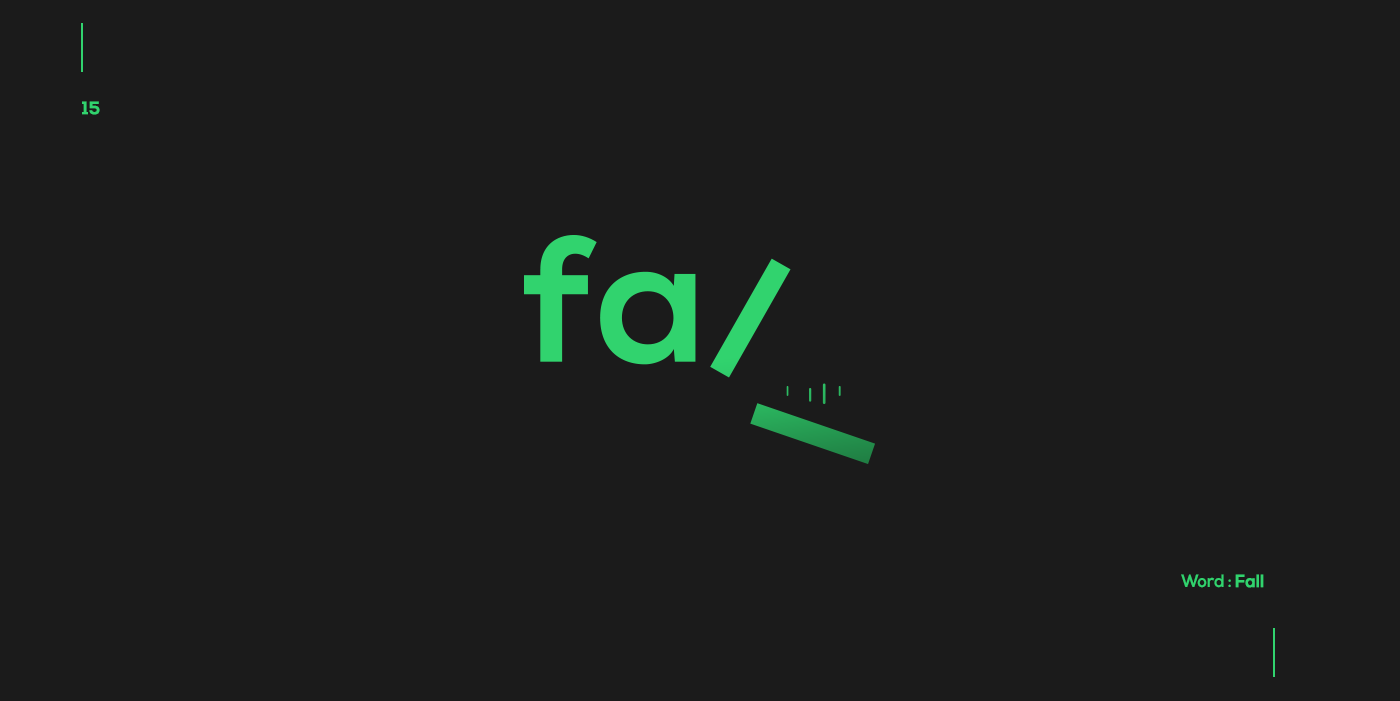
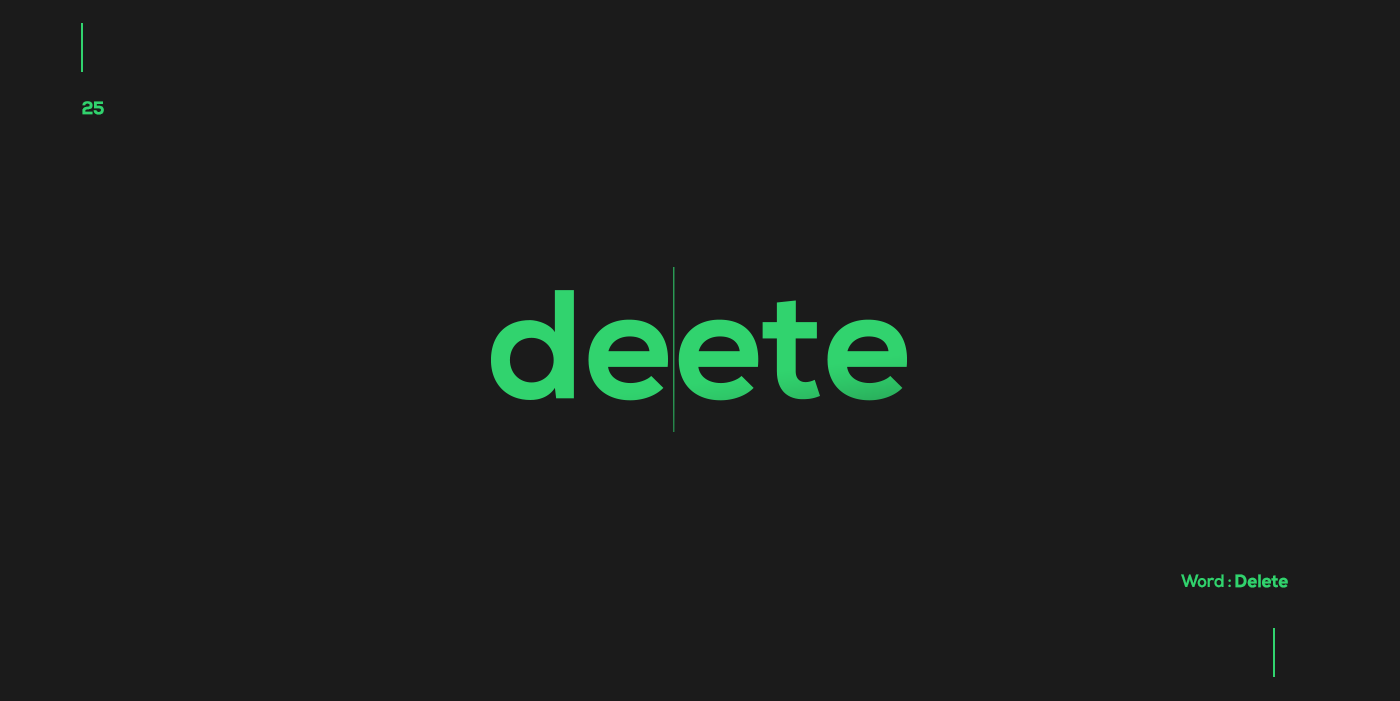
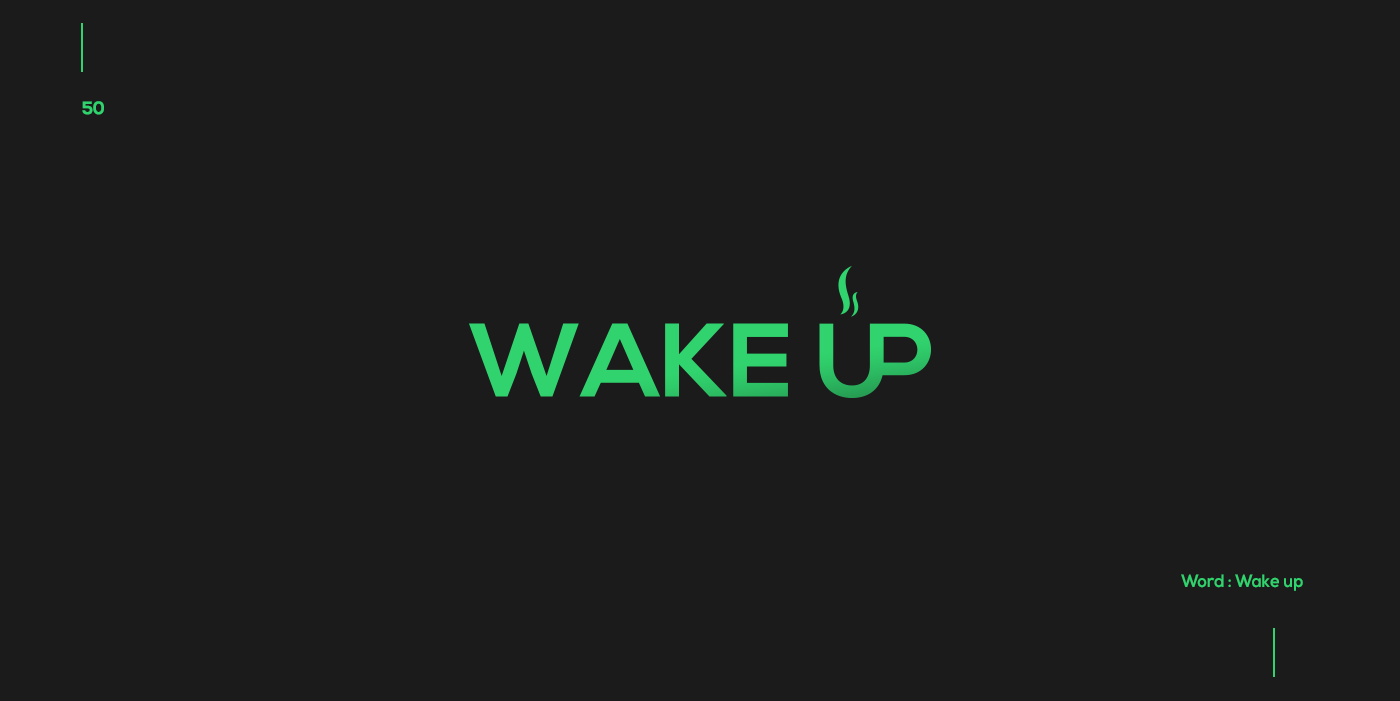
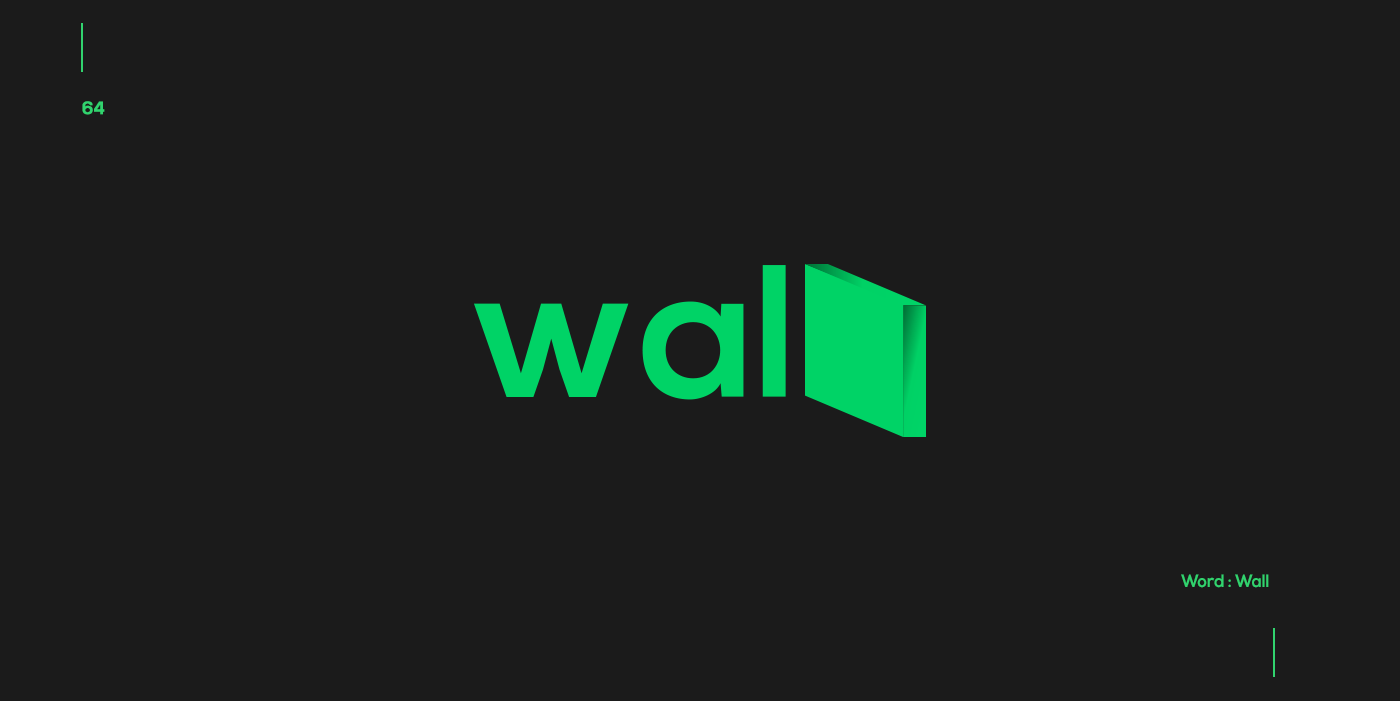
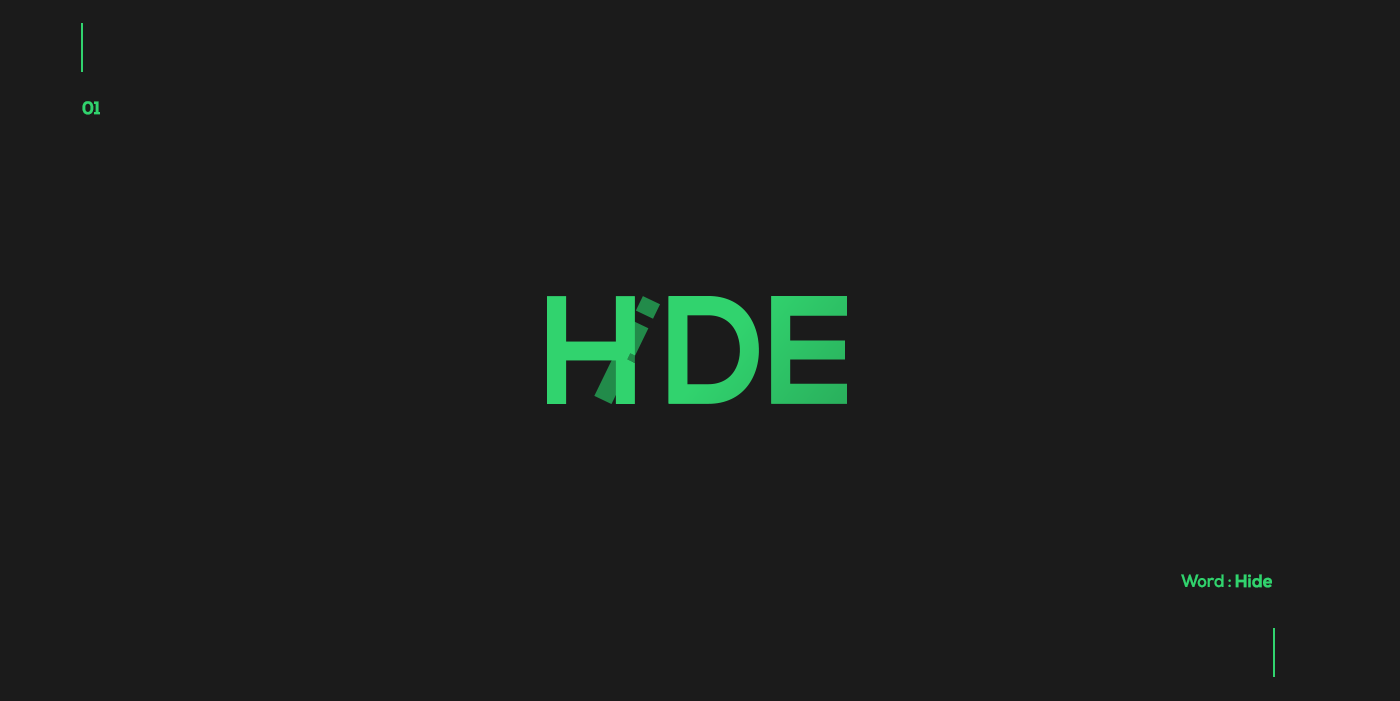
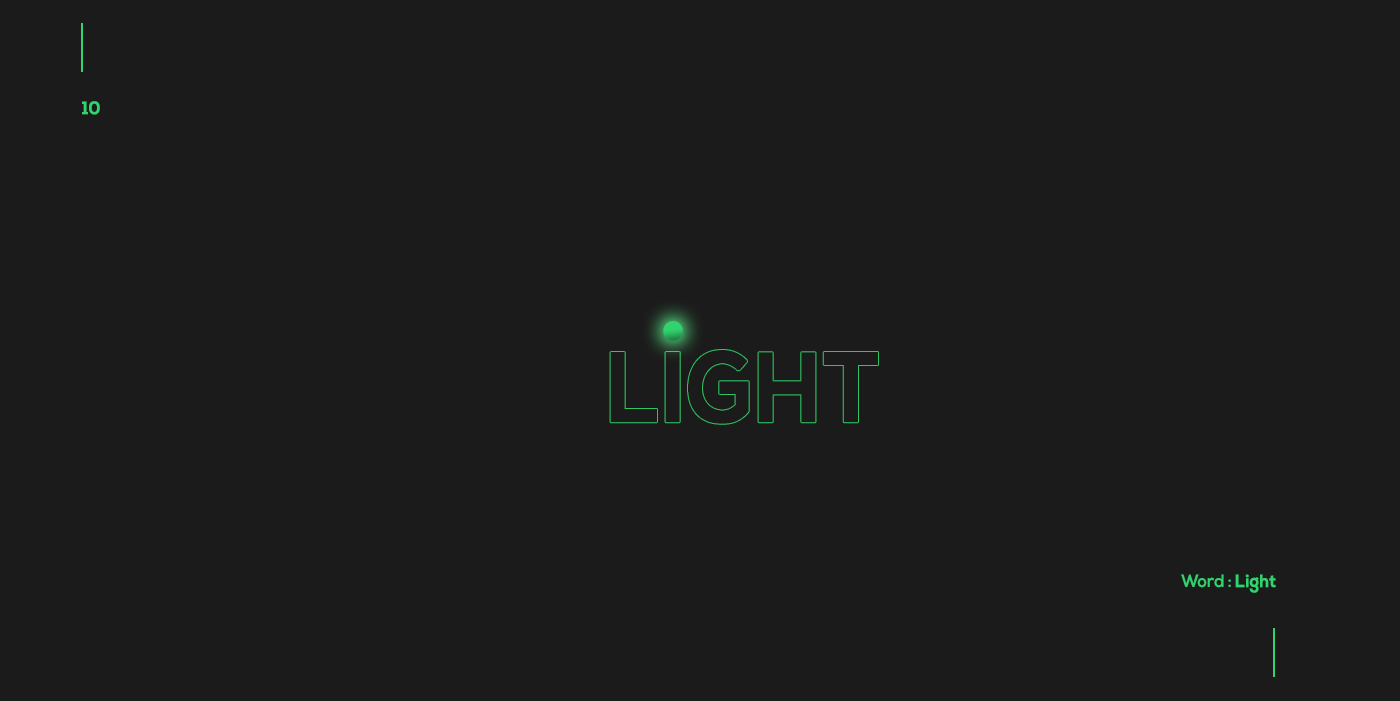
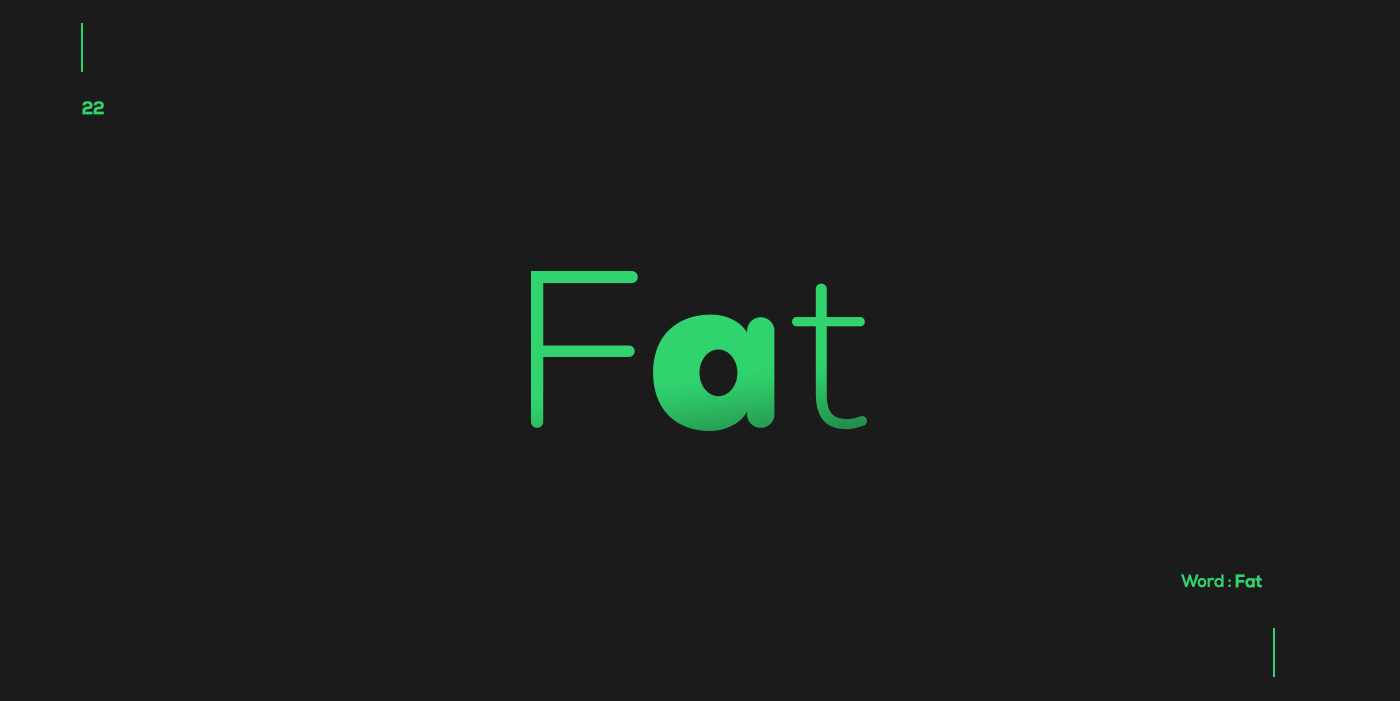
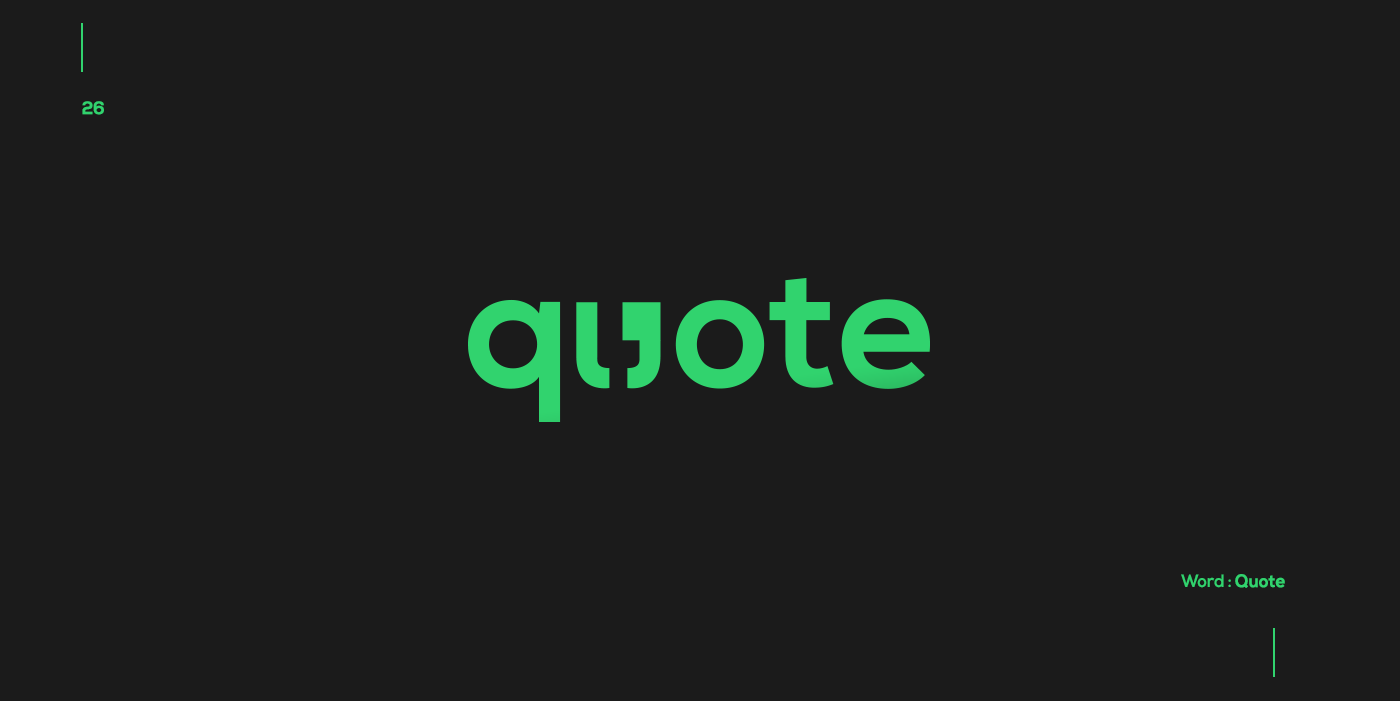
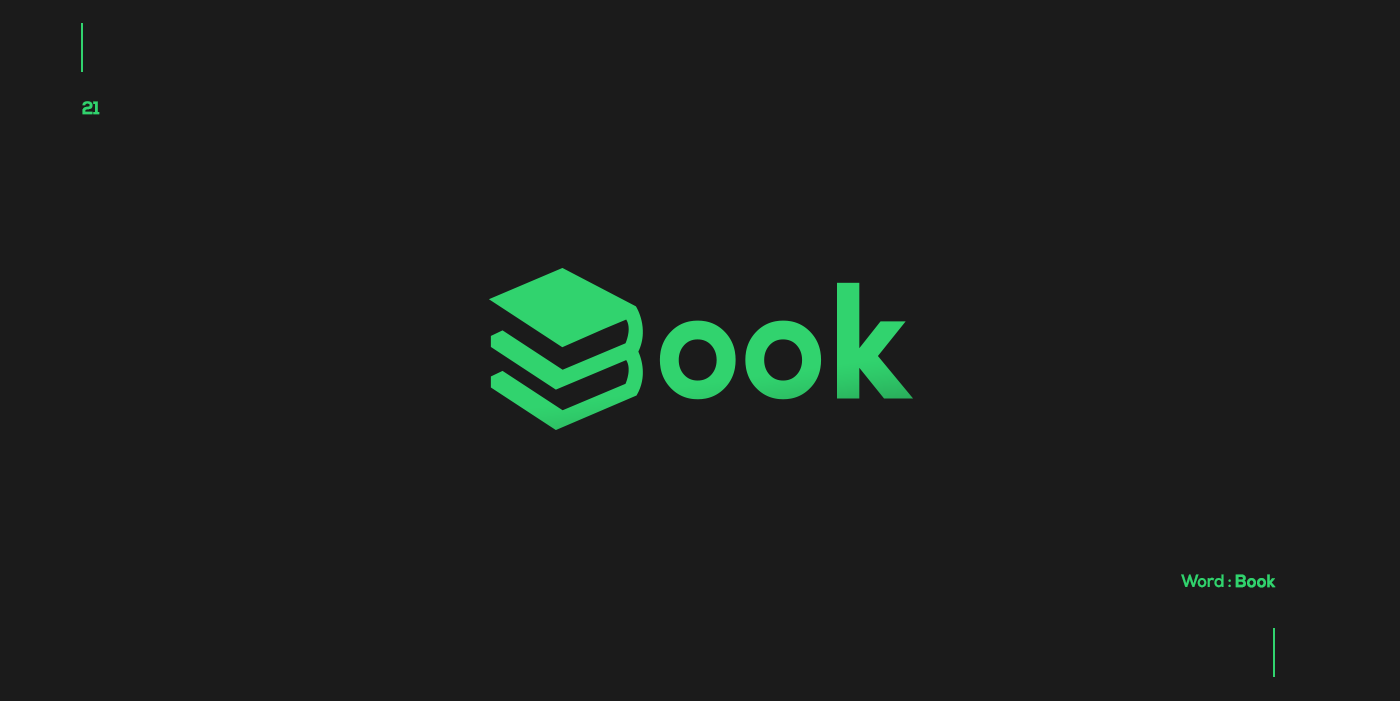
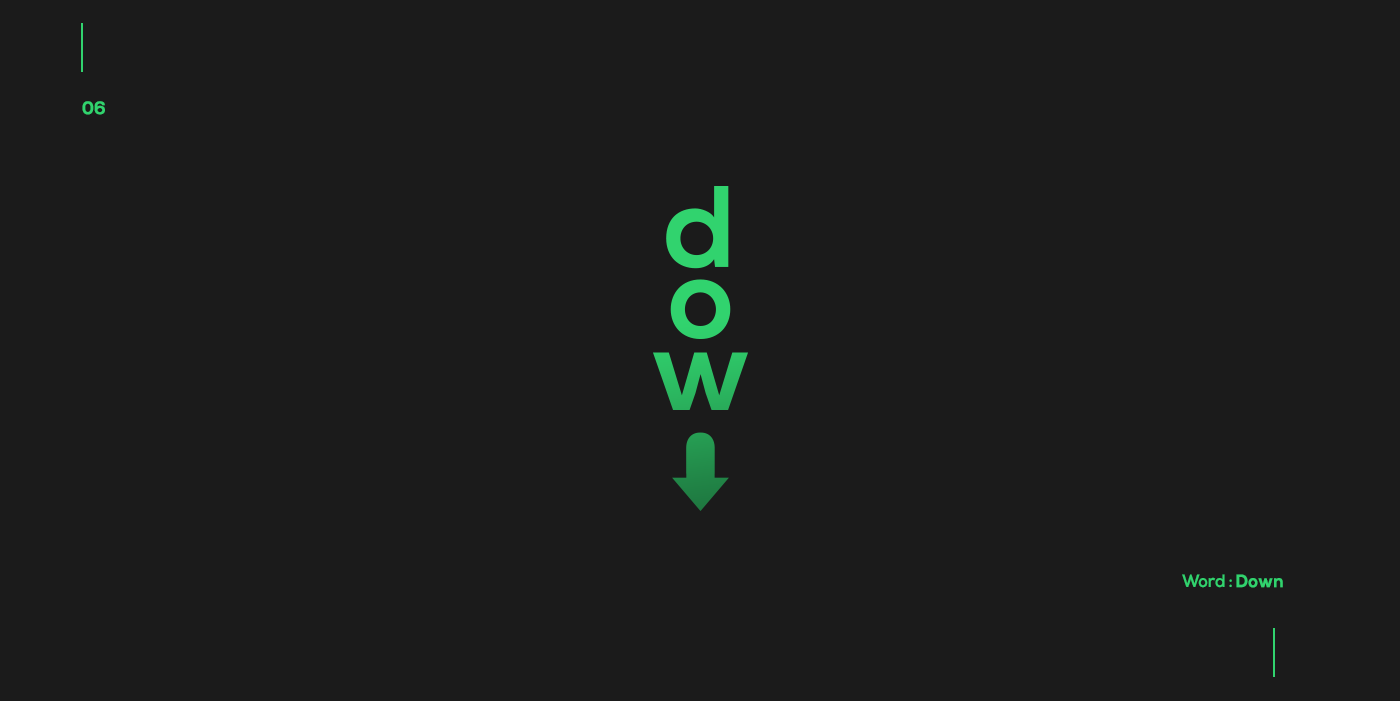
E aí, vamos tentar fazer esse projeto com palavras brasileiras?